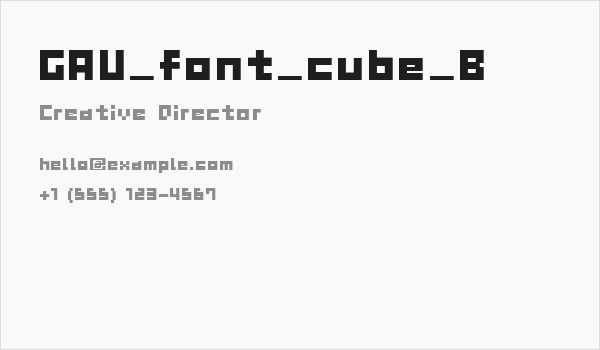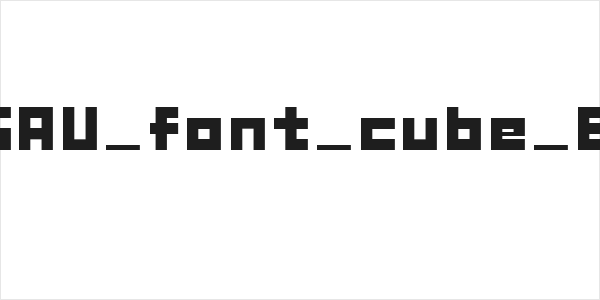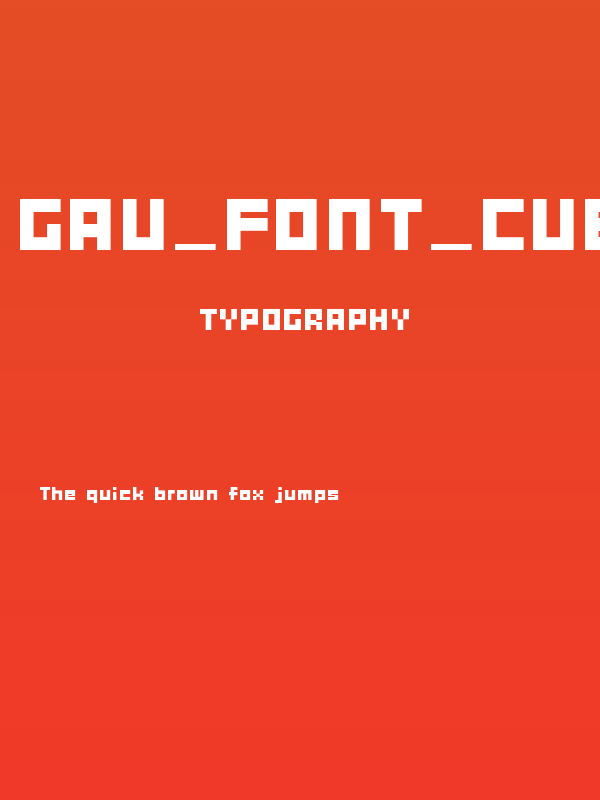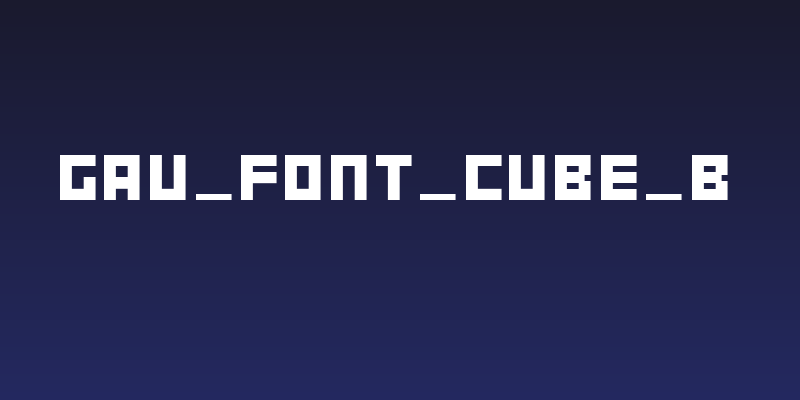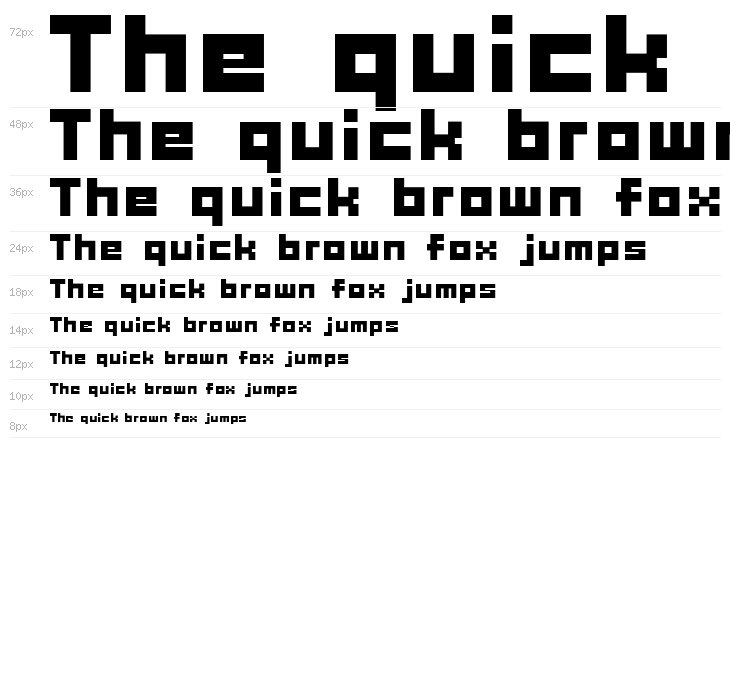
GAU_font_cube_B Font
✎ Pixel
| Gesamtstil | Retro, Digital |
| Anwendungsfall | Logos, Headlines, Posters |
| Vorgeschlagene Projekte | Ideal for video game designs, digital art projects, retro-themed posters, and tech-related branding. |